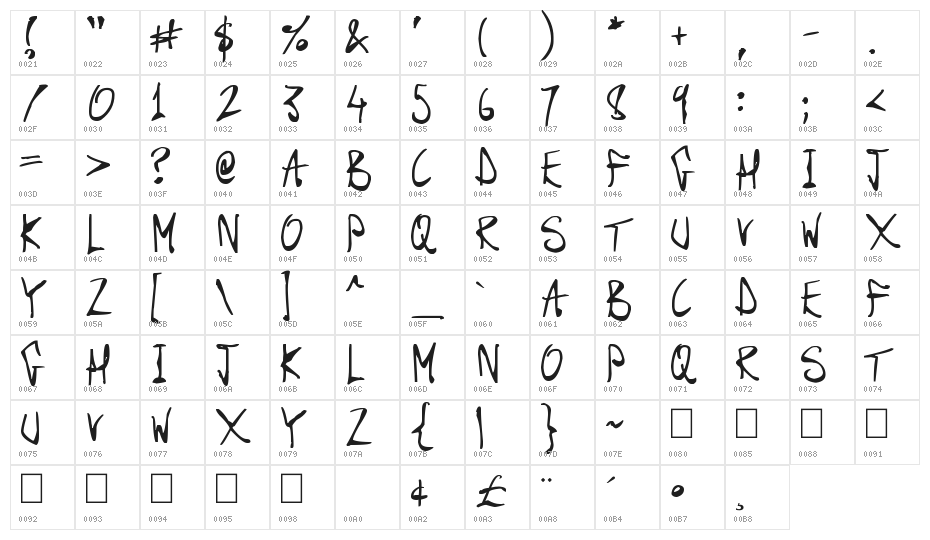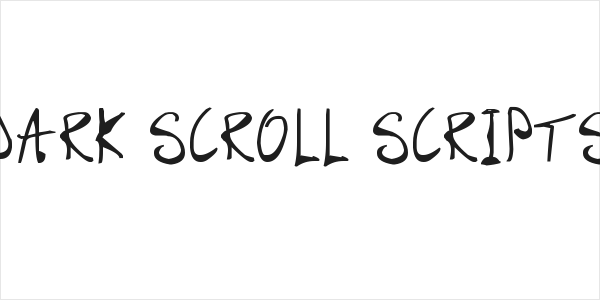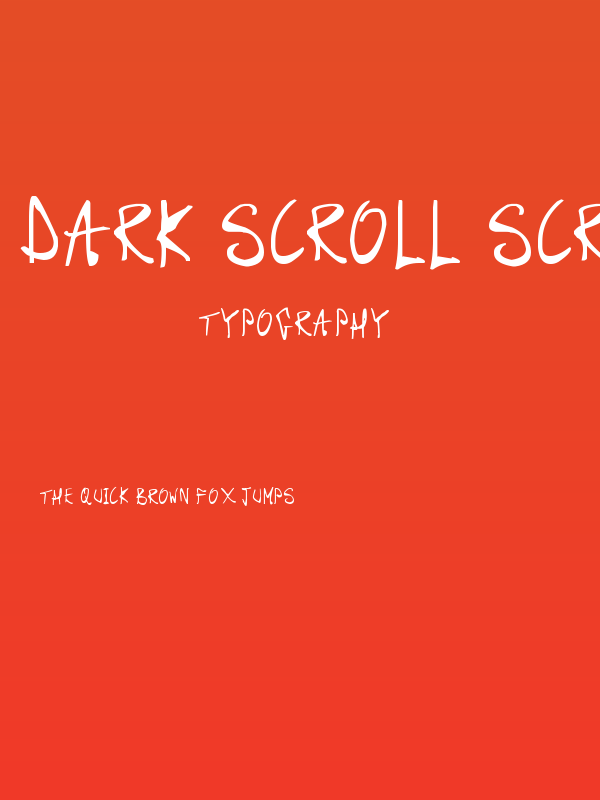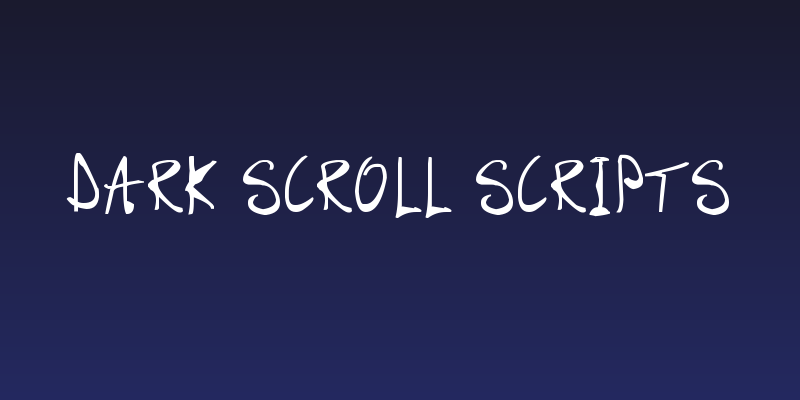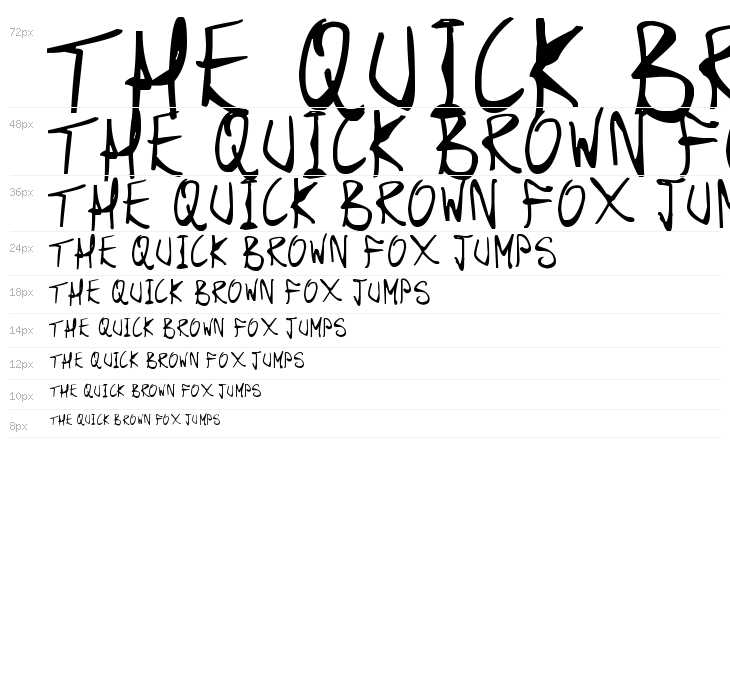
Dark Scroll Scripts Font
| Anwendungsfall | Headlines, Logos, Informal Text |
| Vorgeschlagene Projekte | Ideal for greeting cards, children's books, playful branding, and informal invitations. |